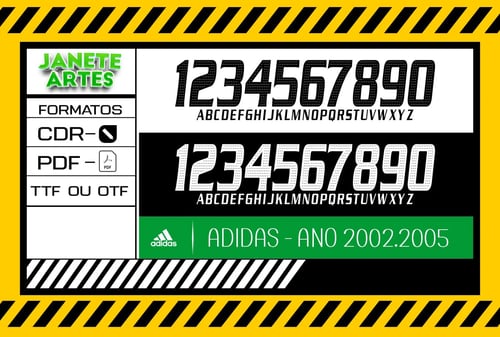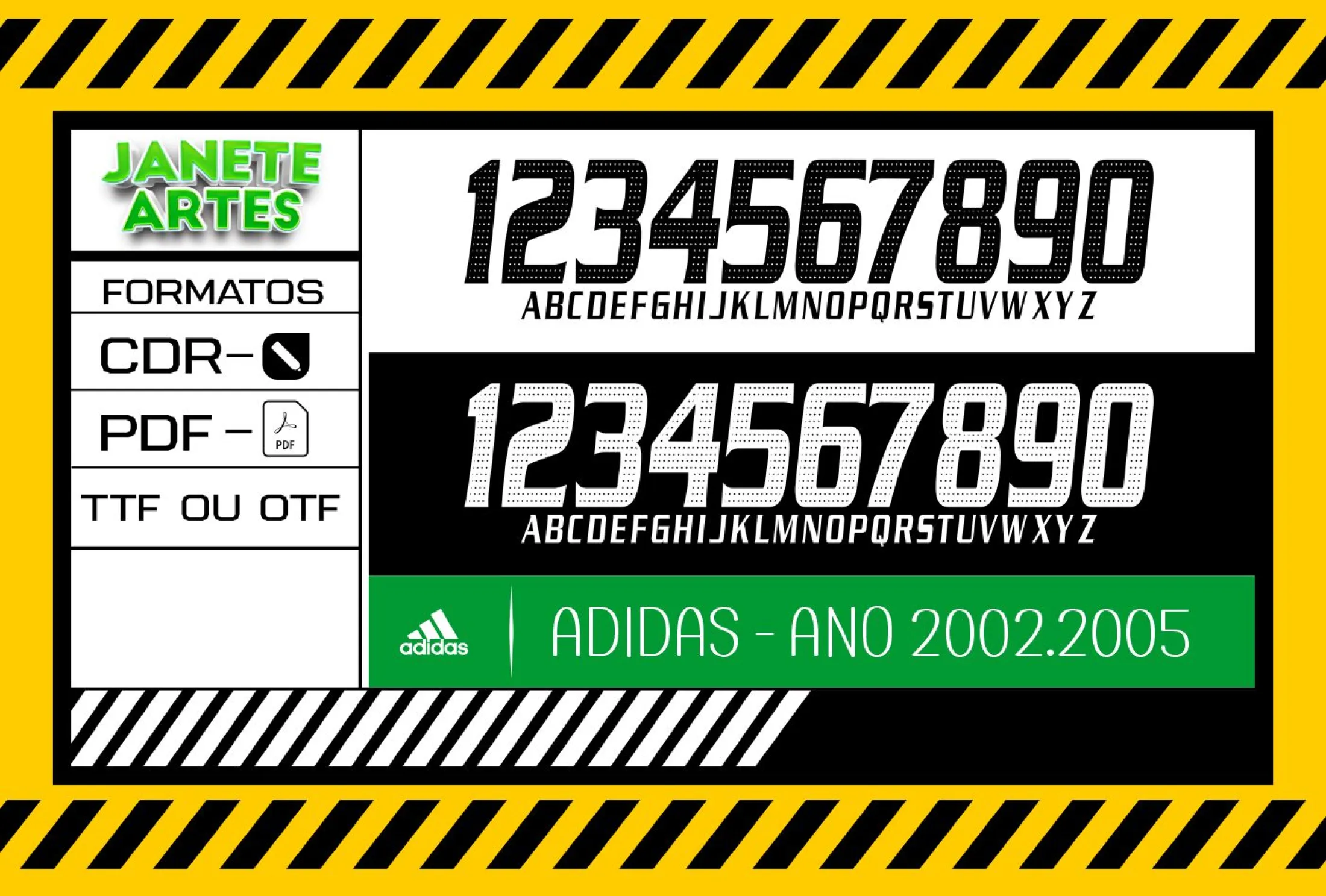
Fonte de Time Tipografia Adidas 2002 - 2005
Uma viagem no tempo com o Arte Fonte de Time Tipografia Adidas 2002-2005 para Camiseta
Imagine aquela tarde no campinho, o som da torcida vibrando e o uniforme que marcou gerações. Foi assim que nasceu a inspiração para o nosso arquivo Arte Fonte de Time Tipografia Adidas 2002-2005 para Camiseta. Essa fonte retrô da Adidas, usada entre 2002 e 2005, traz a nostalgia dos tempos em que cada jogo era uma festa. Se você é fã de futebol, design vintage ou quer reviver essa época, essa é sua chance!
Com o Arte Fonte de Time Tipografia Adidas 2002-2005 para Camiseta, você poderá criar peças únicas e com alto apelo visual, trazendo toda a energia e autenticidade desse clássico.
- Ideal para times amadores, eventos esportivos ou mesmo para fãs do estilo retrô.